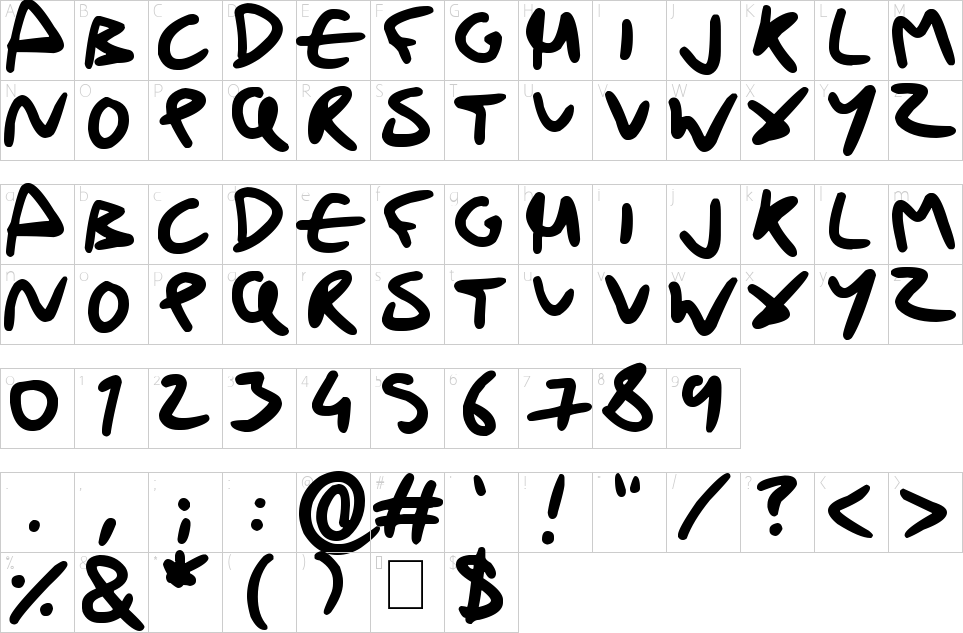
Descubra a sensação engraçada e descontraída do Drunk Handwriting Font, perfeita para personalizar seu design com uma escrita aparentemente embriagada. Desenvolvida por Darrell Flood, esta fonte é ideal para aqueles que buscam algo singular e único para seus projetos digitais. Seja você um designer gráfico, ilustrador ou criativo de qualquer área, Drunk Handwriting pode ajudar a dar uma pitada de humor à sua próxima peça. Suas letras entorpecidas não só deixam seu trabalho com uma personalidade única, mas também garantem que cada projeto seja marcado pela sua originalidade. Com um download fácil e gratuito disponível para Windows e Mac, é simples adicionar esta fonte especial ao seu arsenal de recursos gráficos. Experimente Drunk Handwriting hoje e transforme a maneira como você cria com uma escrita engraçada e única.